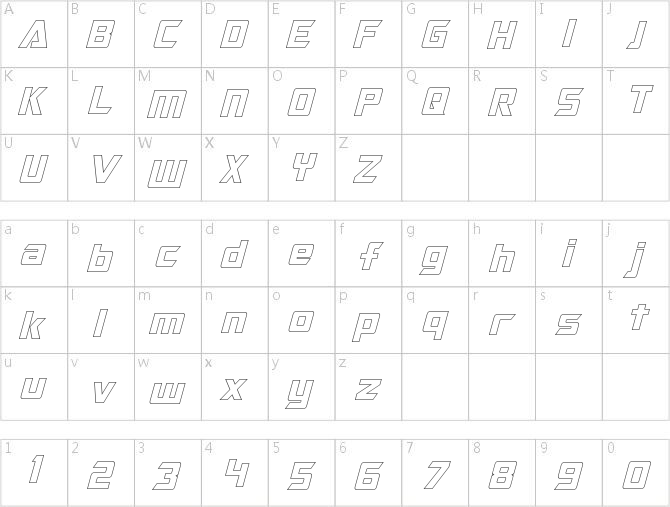
Optimus Hollow Italic 詳情頁(yè)
Optimus Hollow Italic字體字庫(kù)是一款讓人賞心悅目、百看不厭的英文字體,適合各類廣告和產(chǎn)品包裝設(shè)計(jì)應(yīng)用,字體大小0.04MB,格式為ttf字體,上傳用戶是小籃子,作者/版權(quán)方為未知